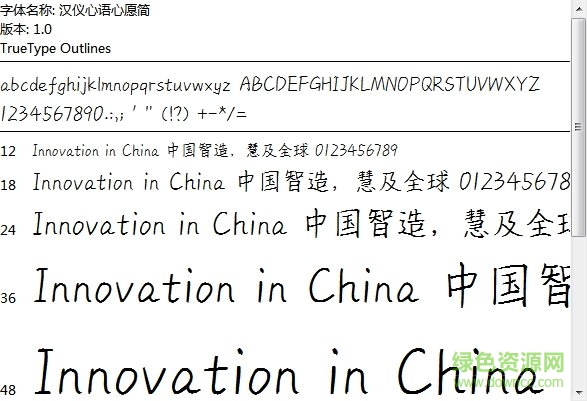
漢儀心語(yǔ)心愿體ttf
漢儀心語(yǔ)心愿體是一款形似楷書(shū)的漢儀字體,整體結(jié)構(gòu)端正精簡(jiǎn),字跡清晰而端正清秀,有著十分悅目的視覺(jué)體驗(yàn),給用戶(hù)的設(shè)計(jì)帶來(lái)多樣選擇,綠色資源網(wǎng)今日推薦!
漢儀心語(yǔ)心愿字體特色
漢儀心語(yǔ)心愿ttf字體,有著完整的字庫(kù),支持中英文輸入,近似楷體的書(shū)法設(shè)計(jì)讓文字更顯大方端正,讓你的藝術(shù)設(shè)計(jì)、廣告設(shè)計(jì)、包裝設(shè)計(jì)等均有著不錯(cuò)的體驗(yàn)!
漢儀心語(yǔ)心愿ttf
漢儀心語(yǔ)心愿體有著手寫(xiě)體的簡(jiǎn)潔干練,也有著藝術(shù)字體的娟秀怡然,藝術(shù)效果非常出色,可以使用各類(lèi)藝術(shù)策劃,有可以安裝在手機(jī)上使用,辨識(shí)性高,讓你的閱讀更加舒適!